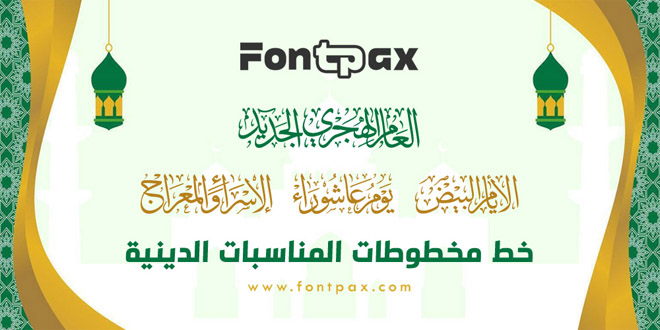
خط مخطوطات المناسبات الدينية .. خط رائع يحتوي على (22) مخطوطة مناسبات دينية يمكن استخدامها في كافة المجالات، تعمل المخطوطات بكتابة الأرقام الإنجليزية من (1) إلى (22)، ويوجد دليل استخدام يوضح الطريقة الصحيحة للاستخدام، وهي متاحة للتحميل المجاني الان.
ملاحظة هامة : الخط يكتب بالأرقام الإنجليزية من (1) إلى (22)